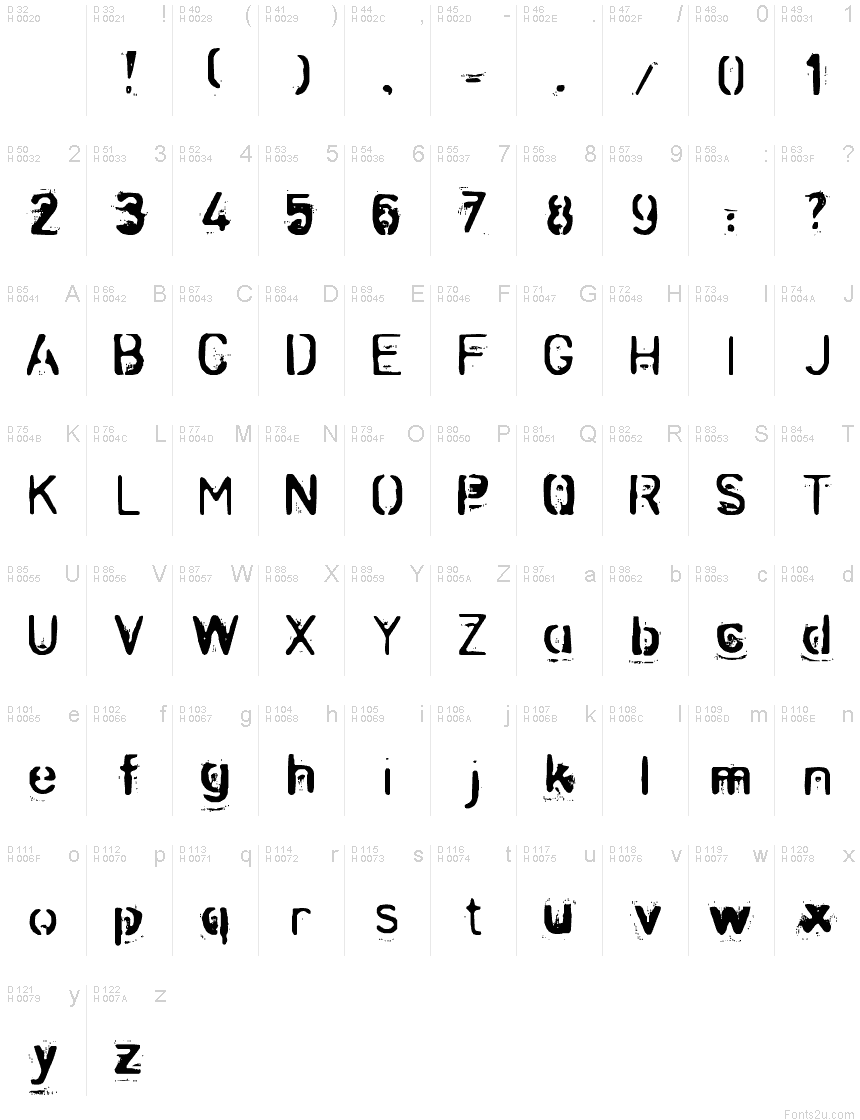
Zombie-Noize autorstwa Mr. Fisk to bezpłatny, zniekształcony krój pisma typu display, utrzymany w stylistyce horror-zinów. Litery wyglądają na wycięte, zapchane i zużyte jednocześnie, łącząc zaokrąglone luki, skapujące pęknięcia i tępe krawędzie w całość, która przypomina połączenie szablonu z efektem wyblakłej kserokopii.
Sprawdzi się idealnie na plakatach, ulotkach zespołów, w tytułach gier, grafikach na imprezy z dreszczykiem czy surowych nagłówkach, gdzie font nie powinien być schludny, lecz niestabilny. Wykorzystaj go do krótkich nagłówków, plansz tytułowych czy napisów w stylu logo, które mogą skorzystać na tych połamanych kształtach i rozmazanych detalach, aby nadać całości klimat lo-fi rodem z horroru.
Zombie-Noize